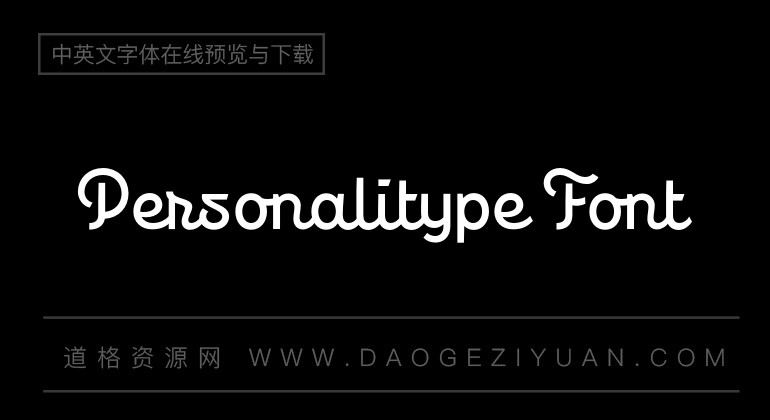
Personalitype Font
Personalitype Font 是一款由设计师 Alexandra Korolkova 和 Maria Selezeneva 设计的字体。这款字体于2018年推出,是一款拥有多种风格和变体的手写字体,适合用于印刷、品牌设计、标志、包装设计、海报等设计项目。此字体的特点是具有浓厚的个性和独特的风格,可以为设计师提供丰富多彩的设计选择,并增强设计作品的品牌认知度。Personalitype Font 包含了不同的风格,包括手写、粗体、斜体、轮廓等。此外,该字体还包含了多种符号和数字,丰富了设计的表现力。总的来说,Personalitype Font 是一款非常实用的字体,可以让设计师在设计中表现出自己的个性和风格。
Personalitype Font是一款非常不错的手写艺术字体,具有很好的视觉感,适合于文化类的宣传设计、商业类品牌的广告和产品包装设计以及个性化文字排版等较多场景。